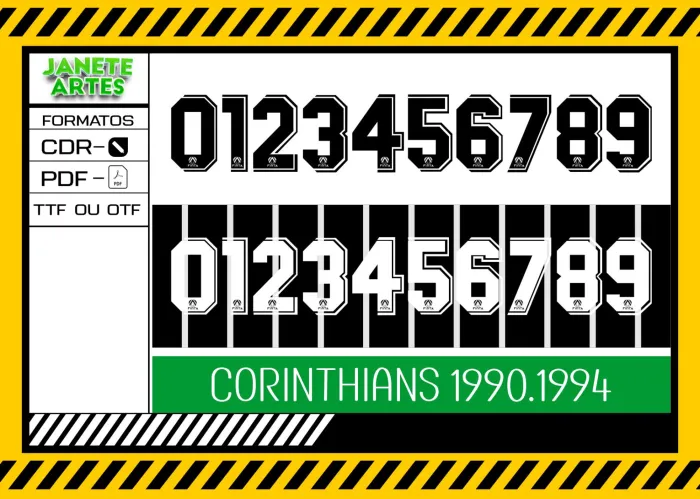
Fonte de Time Tipografia Corinthians 1990 - 1994
Uma vitória para os apaixonados pelo Corinthians
Imagine a emoção de vestir uma camiseta personalizada com a Fonte de Time Tipografia Corinthians 1990 - 1994, resgatando as glórias daquela década de conquistas inesquecíveis. Era um tempo em que o futebol brasileiro vibrava com talento e paixão, e o Timão mostrava sua força nas letras que estampavam os uniformes. Pensando nisso, este arquivo traz para você o design fiel daquele período, para que sua camiseta conte essa história junto com você.
- Ideal para criar camisetas, camisas e blusas com um visual retrô e cheio de personalidade.
- Perfeito para personalizar peças para torcida, eventos esportivos, cursos de design ou colecionadores.
Com a Fonte de Time Tipografia Corinthians 1990 - 1994, você resgata uma era dourada e transforma sua paixão pelo futebol em estilo e autenticidade. Vista sua história no peito e mostre sua paixão com originalidade!